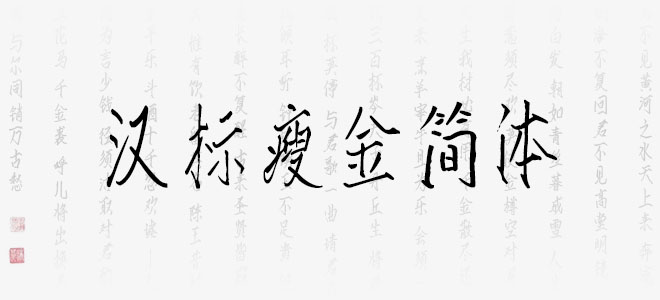
漢標(biāo)瘦金簡體字體加粗了筆畫,筆形和結(jié)構(gòu)高度穩(wěn)定,易讀性強(qiáng)。其風(fēng)格雍容高雅,適用于文化類的宣傳設(shè)計(jì),以及商業(yè)類品牌的廣告和產(chǎn)品包裝設(shè)計(jì),歡迎喜歡漢標(biāo)瘦金簡體的朋友前來下載使用。
漢標(biāo)瘦金簡體